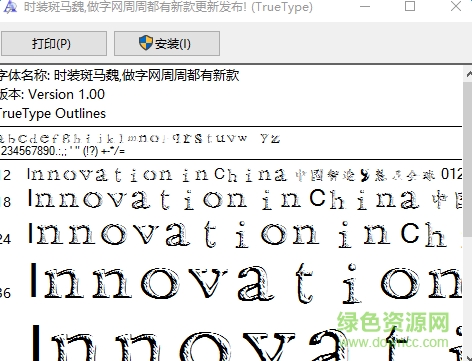
時(shí)裝斑馬魏字體是一款很有個(gè)性的電腦藝術(shù)字體,這款字體寫(xiě)出來(lái)的字是很好看的,也很有特色,用于藝術(shù)設(shè)計(jì)、廣告設(shè)計(jì)等方面都是很不錯(cuò)的,當(dāng)然如果大家喜歡這款字體不管用于什么方面都是可以的,歡迎大家來(lái)綠色資源網(wǎng)下載。
時(shí)裝斑馬魏字體是一款很有特色的時(shí)裝字體,也正是因?yàn)楸容^有特色,所以很多年輕朋友喜歡用,歡迎有需要的朋友來(lái)綠色資源網(wǎng)下載。